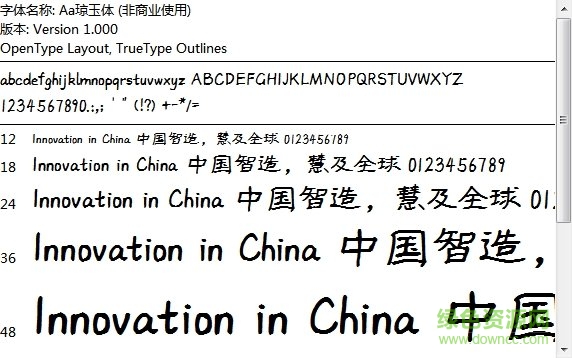
瓊玉體是一款字跡輕簡(jiǎn)、筆觸干凈的手寫字體,讓大家閱讀文字更加舒適和容易辨別,無多余的點(diǎn)綴,文字更顯簡(jiǎn)譜清麗,喜歡的朋友就來綠色資源網(wǎng)體驗(yàn)吧!
瓊玉體深諳手寫體的清晰秀氣,給人十分愉悅的觀賞體驗(yàn),讓文字更具有本身的藝術(shù)審美,可以廣泛運(yùn)用在藝術(shù)設(shè)計(jì)、海報(bào)設(shè)計(jì)等諸多場(chǎng)合。